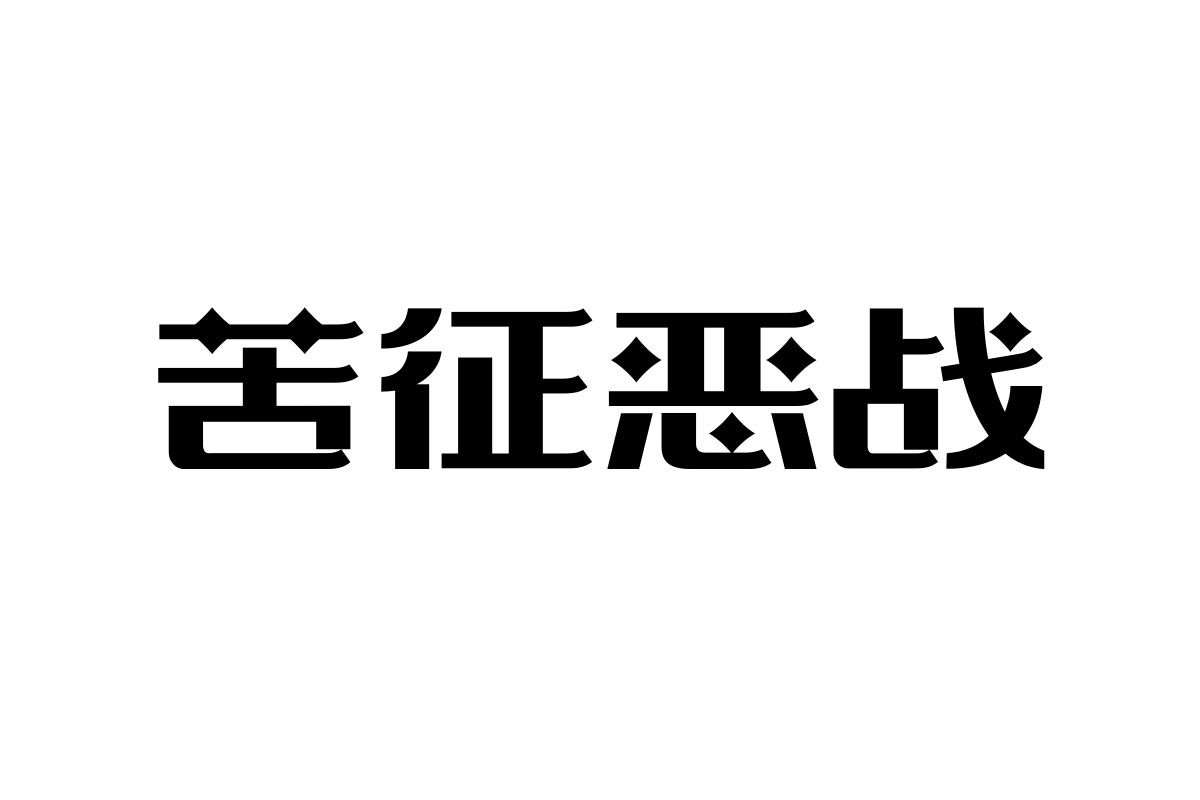
上首奕星体是一款现代中文字体,由上海首奕科技有限公司设计。这款字体以其独特的字形结构和优雅的线条感而受到广泛欢迎。
上首奕星体的笔画流畅自然,结构紧凑有力,给人以强烈的视觉冲击力。其字形呈现出一种简洁而富有张力的风格,适合用于各种文字排版和设计作品。同时,上首奕星体也具有较强的适应性,可以适用于多种场景和场合,如广告、杂志、报纸、网站等。
总的来说,上首奕星体是一款具有很高审美价值和实用性的中文字体,适合用于需要强调视觉效果和传达强烈情感的作品。